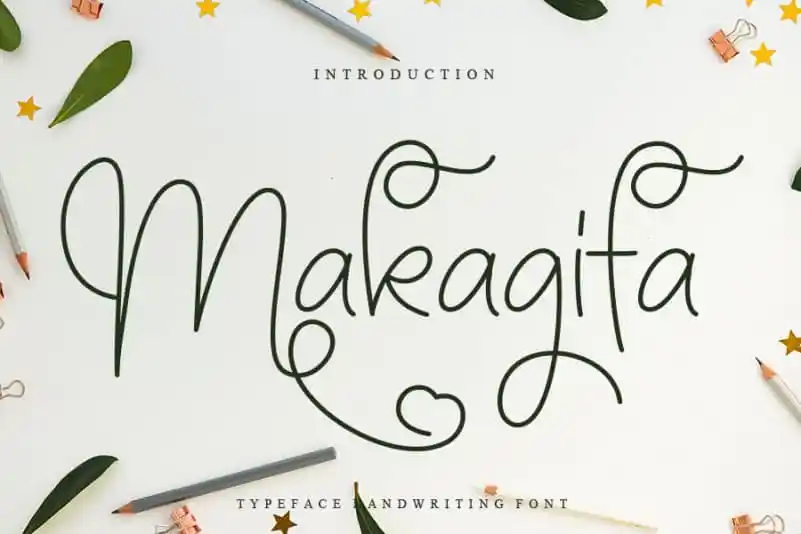
Makagifa Script Font – Fonte Grátis
Makagifa Script Font
A Makagifa Script Font é uma criação de arte única e sofisticada que promete oferecer experiências especiais para os designers digitais. Suas formas fluidas e leves criam um ambiente perfeito para expressar ideias e emoções através do texto, tornando cada design personalizado não apenas visivamente atraente, mas também emocionalmente impactante. A fonte tem uma textura suave e detalhes cuidadosamente concebidos que permitem uma experiência de escrita fluida e precisa, independente da tipografia ou língua usada. Para designers atentos à perfeição visual, essa fonte é como um presente para os olhos – um desfraldar de formas elegantes em cada letra, garantindo que qualquer projeto seja notado. Não hesite em experimentá-la; Makagifa Script Font é mais do que uma opção de fonte, ela se torna uma parte vital da sua identidade visual e criativa.